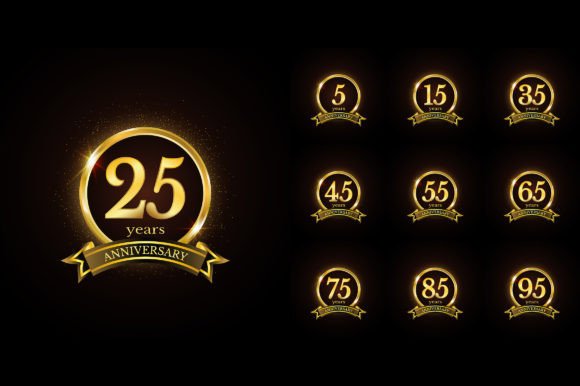
Anniversary Number Logotype Label Badge
การค้นหาองค์ประกอบการออกแบบที่เหมาะสมอาจเป็นเรื่องท้าทาย แต่ Anniversary Number Logotype Label Badge นำเสนอคอลเลกชันที่โดดเด่นซึ่งช่วยยกระดับงานของคุณได้ทันที
สร้างขึ้นอย่างแม่นยำ Anniversary Number Logotype Label Badge ให้เวกเตอร์ที่สะอาด พิมพ์ตัวอักษรที่ราบรื่น และใบอนุญาตเชิงพาณิชย์เพื่อความสบายใจ